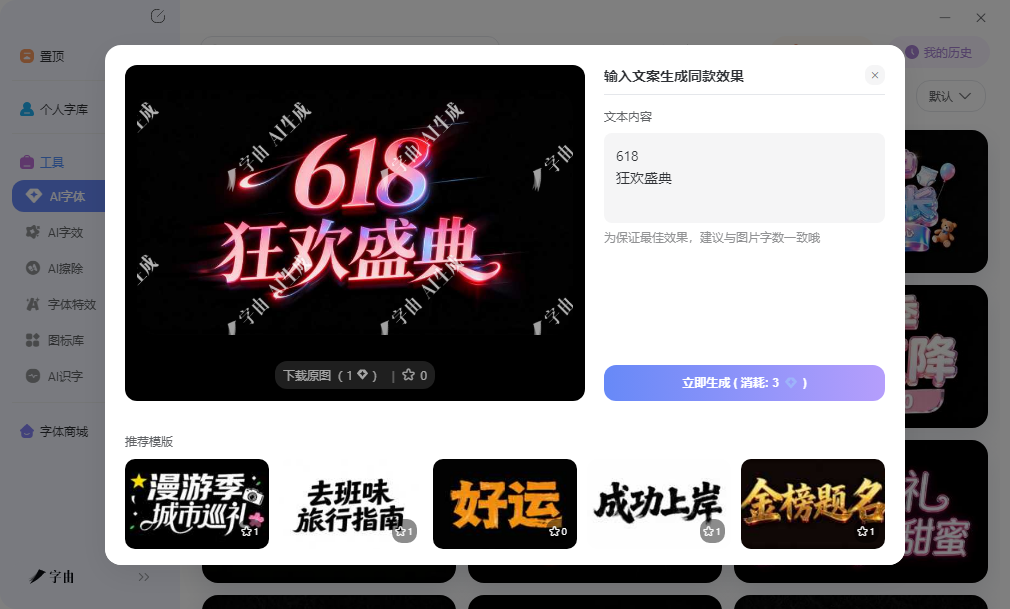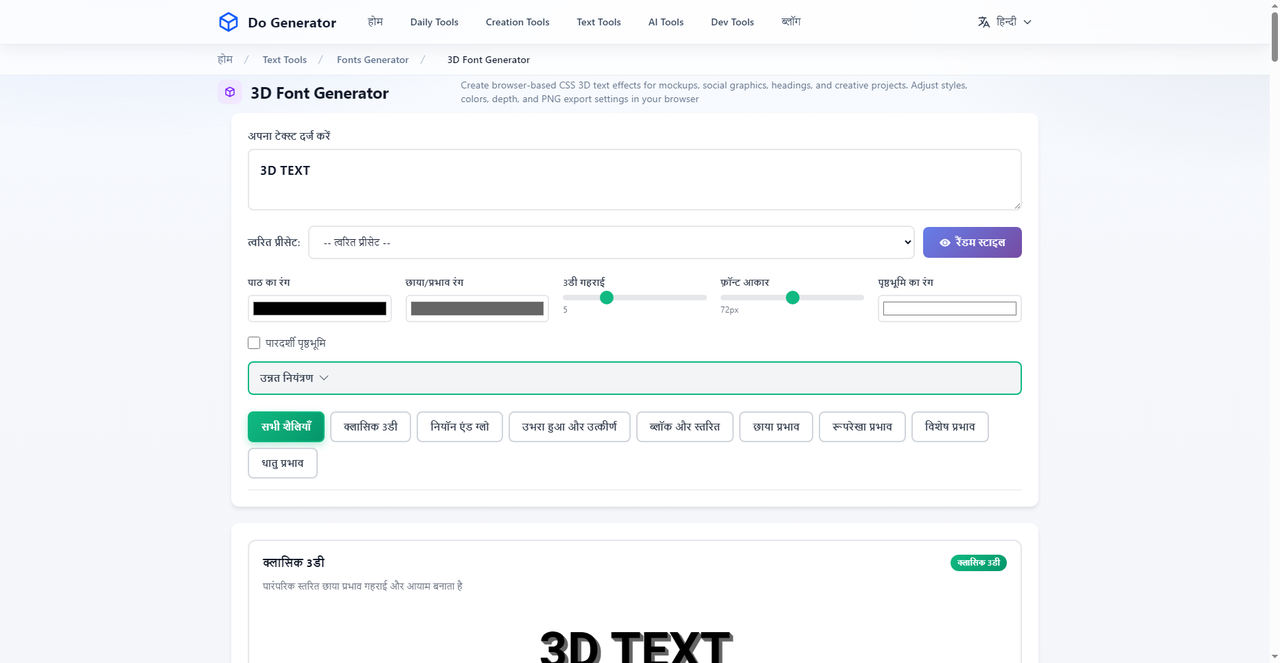
在线创意字体生成器推荐,艺术字体模板随你挑
很多人在做海报、PPT 或者社交媒体配图时,总觉得系统自带的字体不够用,想要一些更有设计感的文字效果。去网上搜创意字体,往往要下载安装包,还要担心版权和兼容问题,好不容易装好了,发现跟设计软件版本不匹配,又得重新找。其实现在有不少创意在线字体生成器可以直接在浏览器里完成效果预览和输出,不需要安装任何软件,打开网页输入文字就能看到效果。这篇文章就整理了几个实用的平台,覆盖字体管理、特效生成、AI 创作和样式转换等多个方面,帮你快速找到合适的方案。
很多人想做带特效的海报标题,第一反应是打开设计软件调图层样式,但对临时做图的人来说,装软件本身就是门槛。字由的 AI 字效功能把这个流程简化了,它本质上就是一个创意在线字体生成器,打开客户端就能直接出图。
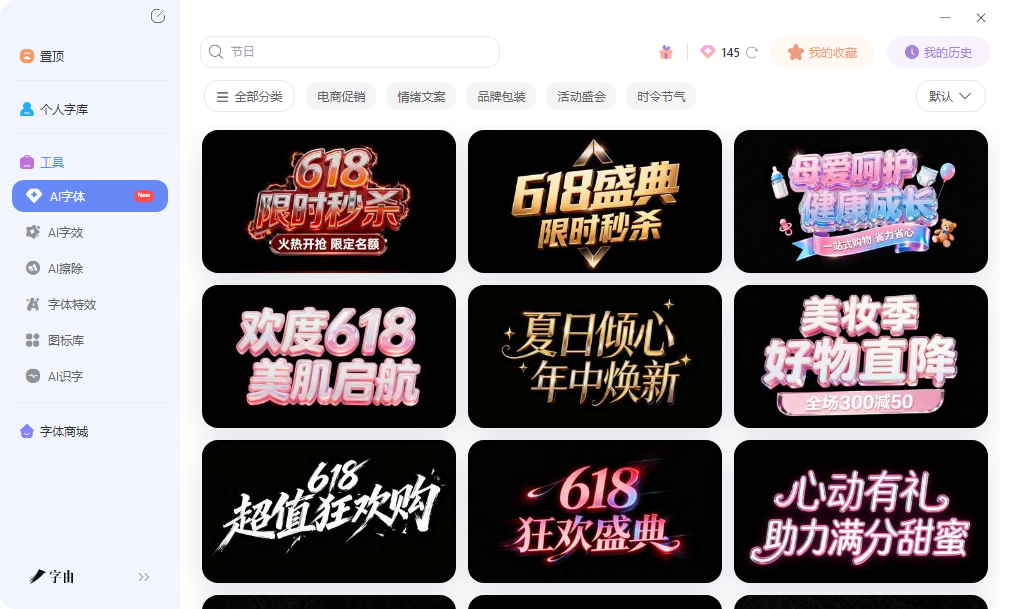
AI 字效内置了丰富的模板,覆盖立体、金属、霓虹、投影、描边等风格。操作流程很直接,在模板库选一个样式,输入文字,点击生成,系统返回带特效的 PNG 图片,背景透明,可以直接拖进 PPT、Photoshop 里叠加使用,不需要抠图。做公众号封面、电商标题、活动海报都很方便。
对于系列物料,字由这个创意在线字体生成器也很实用。固定选一个模板,分别输入不同文案批量生成,风格不会跑偏。这种重复性工作在传统软件里需要反复调图层、导出,而在字由里就是输入文字、点生成、下载,循环很快。
模板库会定期更新新样式,长期做运营物料时可以换版新特效保持新鲜感。模板支持按商务、卡通、现代、复古等分类浏览,不需要在海量模板里逐页翻找。基础功能开放试用,部分高级模板可能需要会员。如果你正在找一个不用装专业软件就能出艺术字效果的工具,字由这个创意在线字体生成器基本覆盖了从选字到出图的全流程,在浏览器里就能完成。
2、3D Font Generator
这是一个专攻立体的创意在线字体生成器。它的界面很直接,输入文字之后,可以调整颜色、深度、阴影角度、背景透明度等参数,实时看到立体效果。所有调整都在浏览器里完成,不需要安装任何软件。这个工具适合需要快速获得立体文字素材的场景,比如海报标题、社交媒体封面、PPT 标题页。调整好参数后,可以直接导出 PNG 图片,分辨率足够在网页和屏幕展示中使用。因为是基于 CSS 渲染,效果比较干净,边缘锐利,不会出现低分辨率位图的锯齿问题。
不过它的功能相对单一,就是生成 3D 文字图片,不提供可安装的字体文件,也不支持批量处理。如果你正在找一个能出 3D 效果的创意在线字体生成器,它的效率很高;但如果需要整套字体或者反复编辑文字内容,就不太合适了。
3、Font Generator
Font Generator 是另一个轻量级的创意在线字体生成器,主打装饰性文字样式的快速预览和复制。首页把字体按 Bold、Cursive、Gothic、Calligraphy、Fancy 等类型做了分类,你可以先选一个大类,再浏览具体的样式变体。使用方式很简单,在输入框里打字,页面会实时显示这段文字在不同样式下的效果。看到喜欢的,直接点击复制按钮,就能把转换后的文字粘贴到社交媒体、聊天软件或者文档里。这种即时复制的设计很适合需要快速发一条带特效文字的动态,或者给昵称、标题加点装饰感。
需要注意的是,Font Generator 生成的结果本质上是 Unicode 字符的特殊变体,不是真正的字体文件。
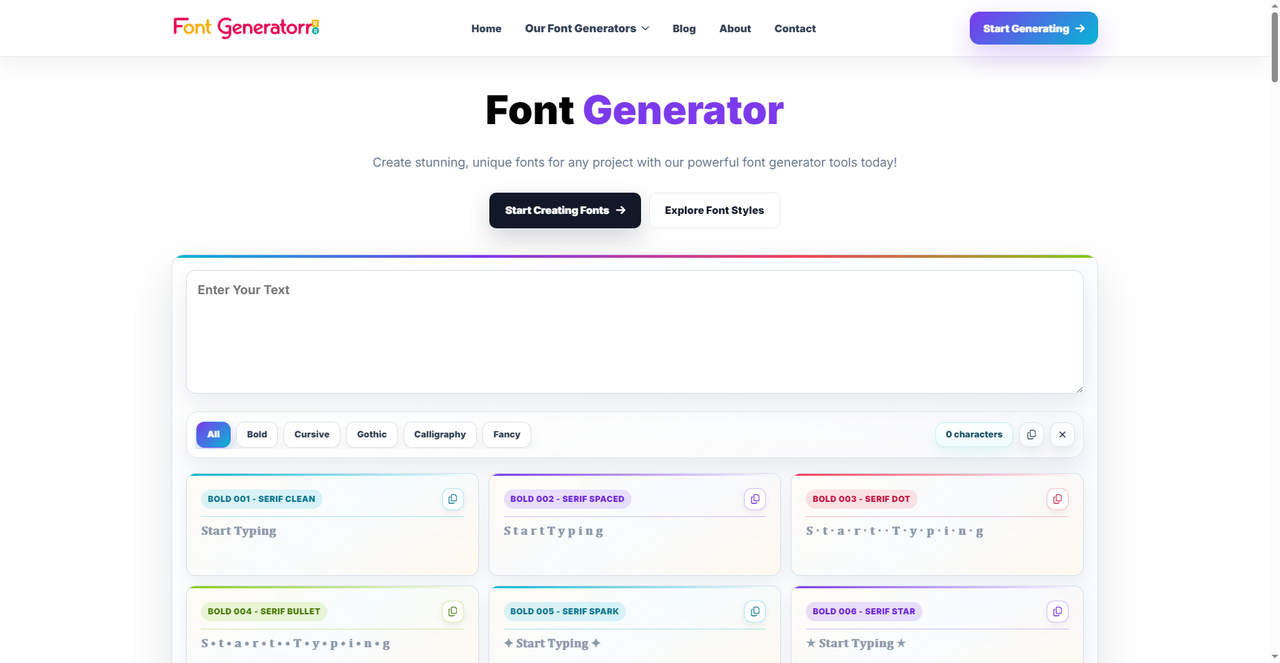
4、Font Max
Font Max 同样属于创意在线字体生成器的范畴,它的特点是收录的样式数量比较多,目前有超过 170 款效果,涵盖 Fancy、Cool、Cursive、Small、Bold、Glitch、Letter Cases、Sym 等 10 种风格分类。操作逻辑和类似的复制工具一致,输入文字后页面会批量展示各种效果预览,每个样式旁边都有独立的复制按钮。你可以快速对比同一句话在不同风格下的视觉差异,然后选择最符合当前场景的一款复制使用。Font Max 的样式数量比较多,尤其是 Glitch 故障风和 Sym 符号替换类的效果,在同类工具里算是特色。
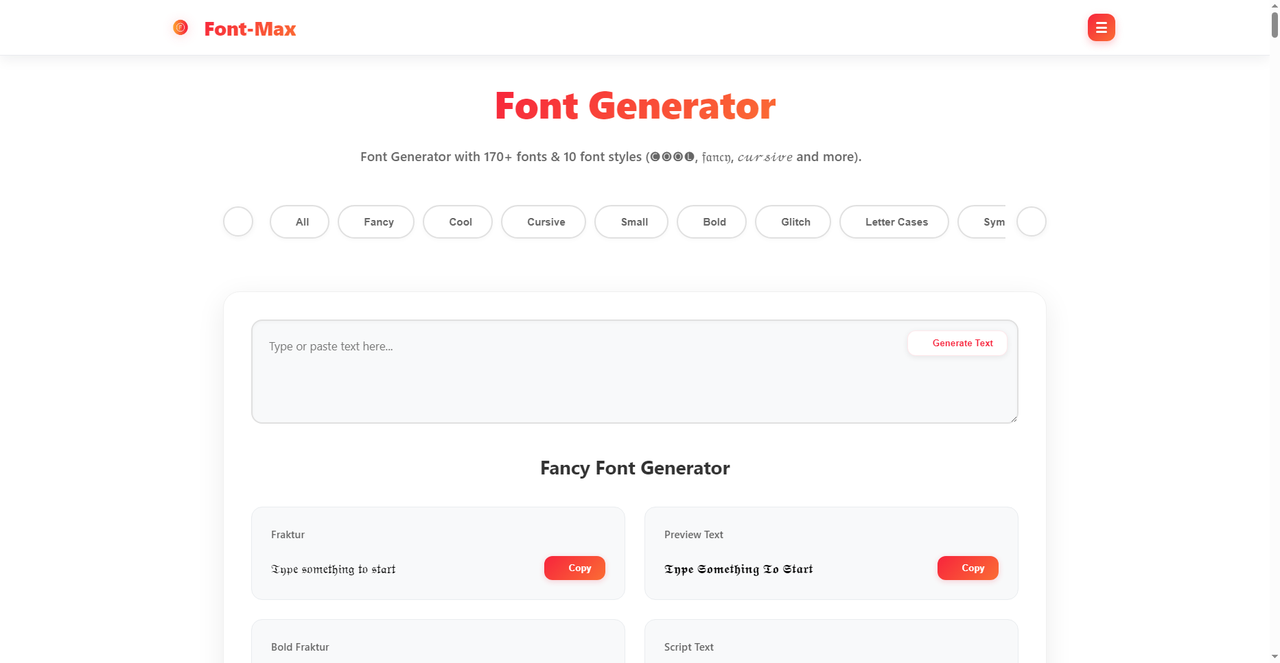
5、Lipi.ai
Lipi.ai 则代表了另一种方向,它用 AI 来生成完整的字体文件,而不是在现有字体上加特效。你可以输入描述性的关键词,比如现代无衬线、古典衬线、手写风格等,AI 会根据提示生成对应的字体字形。
生成完成后,Lipi.ai 支持导出 TTF、OTF、WOFF、WOFF2 等常见字体格式,这意味着你真正获得了一套可以在电脑上安装、在设计软件里调用的字体文件。平台提供了 Modern Sans、Classic Serif 等基础风格选项,生成过程中有实时预览窗口,你可以在看到效果后再决定是否导出。
这种 AI 生成字体的方式和传统字库采购完全不同,它适合需要独特品牌字体但又不想支付高昂定制费用的初创团队或者个人创作者。不过目前 AI 生成字体的质量稳定性还在提升阶段,部分复杂字形或者小字号显示效果可能需要人工调整。如果你需要一个能产出原创字体文件的创意在线字体生成器,Lipi.ai 值得尝试。平台需要注册账号才能使用,部分高级功能可能涉及付费。
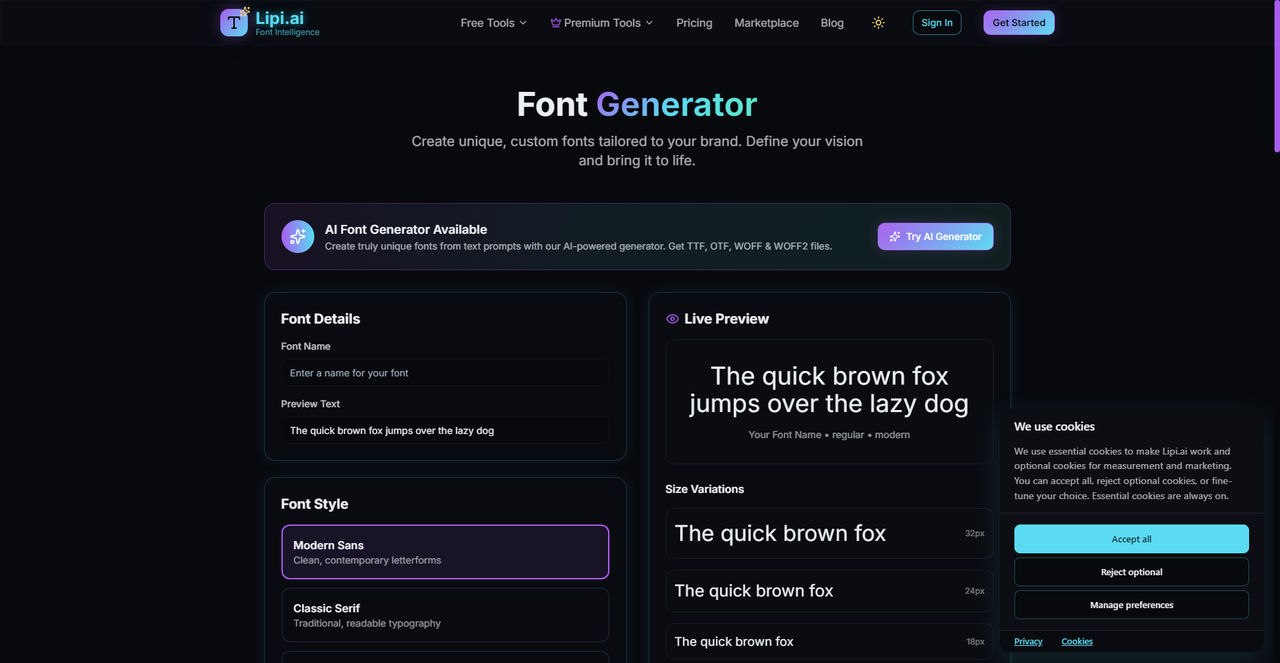
如果你需要系统级的字体管理和跨软件调用,字由的综合能力更强;如果只是临时需要某个特效文字或者装饰性文案,上述几款创意在线字体生成器都能快速解决问题。其余四款工具的共同点是均聚焦于单一生成或转换功能,无法提供系统级的字体管理和跨软件即时调用能力,且输出的结果多为图片或特殊字符,适用场景相对有限。